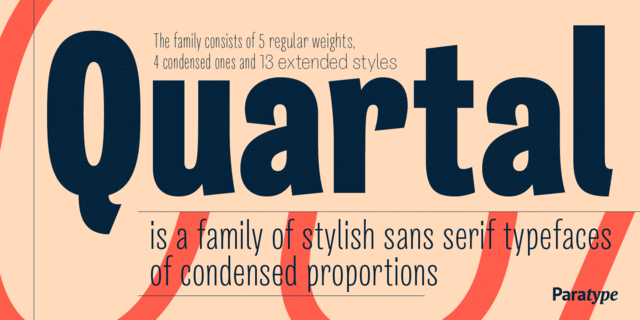
Шрифт Quartal (Квартал) — современный изящный рубленый шрифт зауженных пропорций. Гарнитура состоит из пяти нормальных начертаний разных насыщенностей, четырех узких и тринадцати расширенных, которые по обычным меркам были бы как раз нормальными. Первоначально предполагалось выпустить только узкий вариант, предназначенный для заголовков и рекламных надписей, но в процессе проектирования были добавлены слегка расширенные начертания, что увеличило сферу применения шрифта за счет возможности использования в более мелких кеглях, а позже в 2011 году появились еще более широкие начертания в 7 насыщенностях, к шести из которых были нарисованы курсивы. Эти добавки сильно запутали номенклатуру шрифтовой гарнитуры, но сделали ее более развитой и более универсальной. Название Квартал связано с урбанистическим характером шрифта, что ассоциируется в представлении автора с городским кварталом, полным светящейся рекламы, вывесок, перетяжек и т.п. В комплект знаков Квартала входят алфавиты языков Западной Европы и стандартная кириллица. А кроме того, он содержит некоторое количество альтернативных вариантов знаков. Может использоваться для набора не очень длинных текстов в рекламе, акциденции и журнальной продукции. Дизайн выполнен Олегом Карпинским. Первая версия из 9 начертаний была выпущена компанией ПараТайп в 2010 году, расширенная версия — в 2011 году.